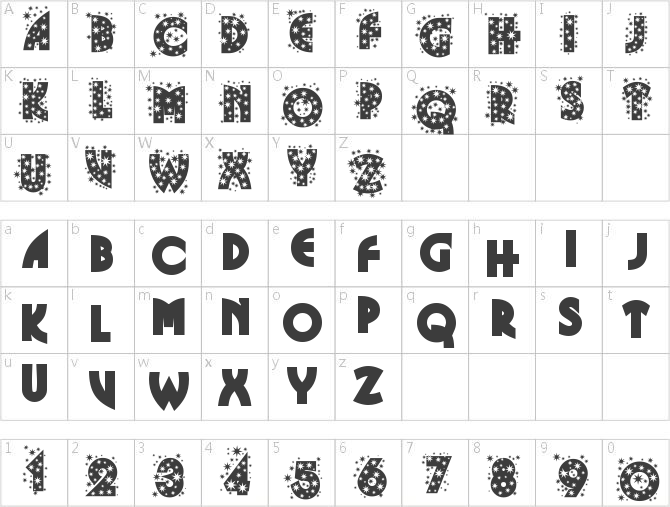
字體名稱: Glitter
Glitter Font
Glitter Font介紹
Glitter Font字體字庫(kù)是一款讓人賞心悅目、百看不厭的英文字體,適合各類廣告和產(chǎn)品包裝設(shè)計(jì)應(yīng)用,字體大小0.06MB,格式為ttf字體,上傳用戶是華大文化傳媒,作者/版權(quán)方為未知